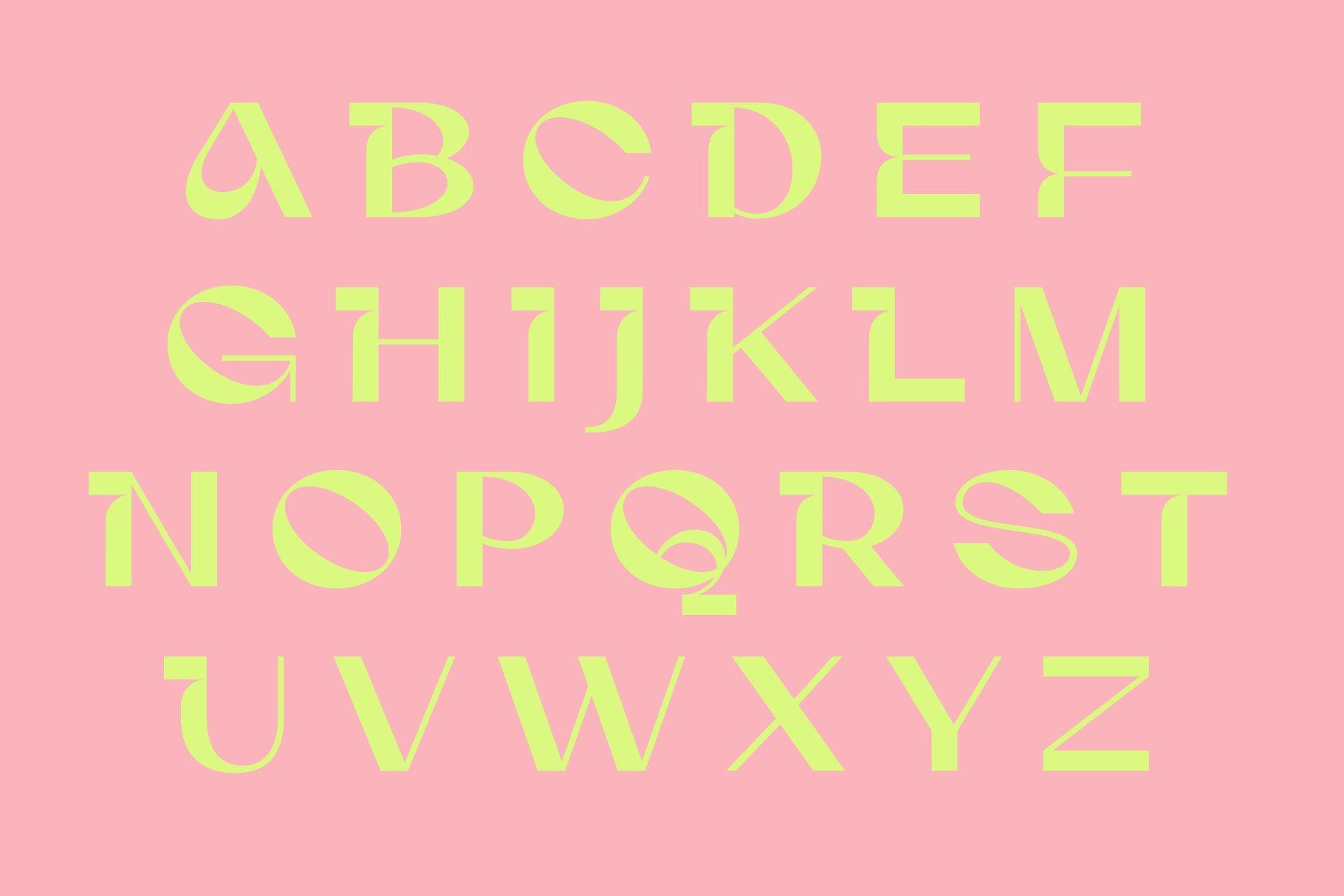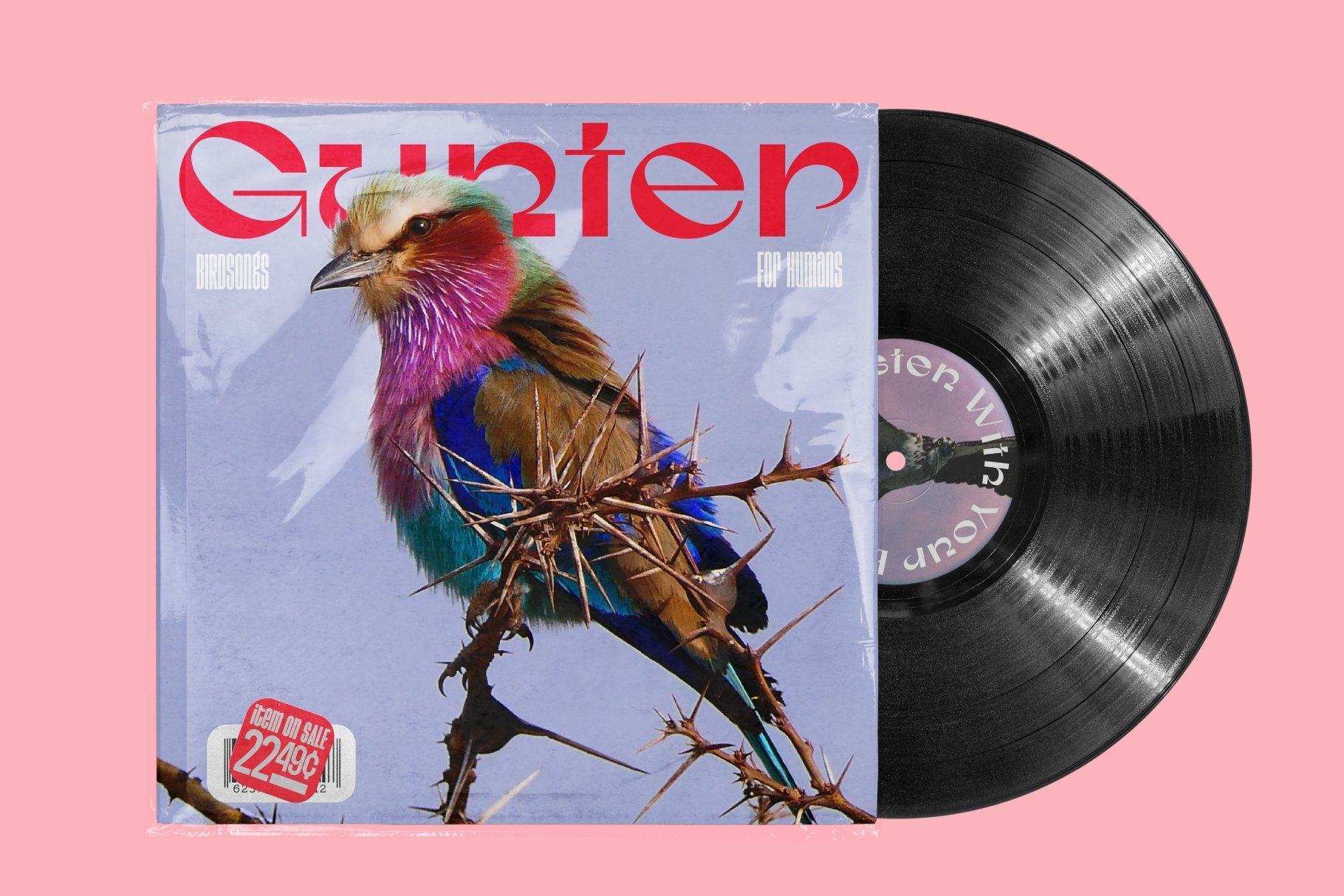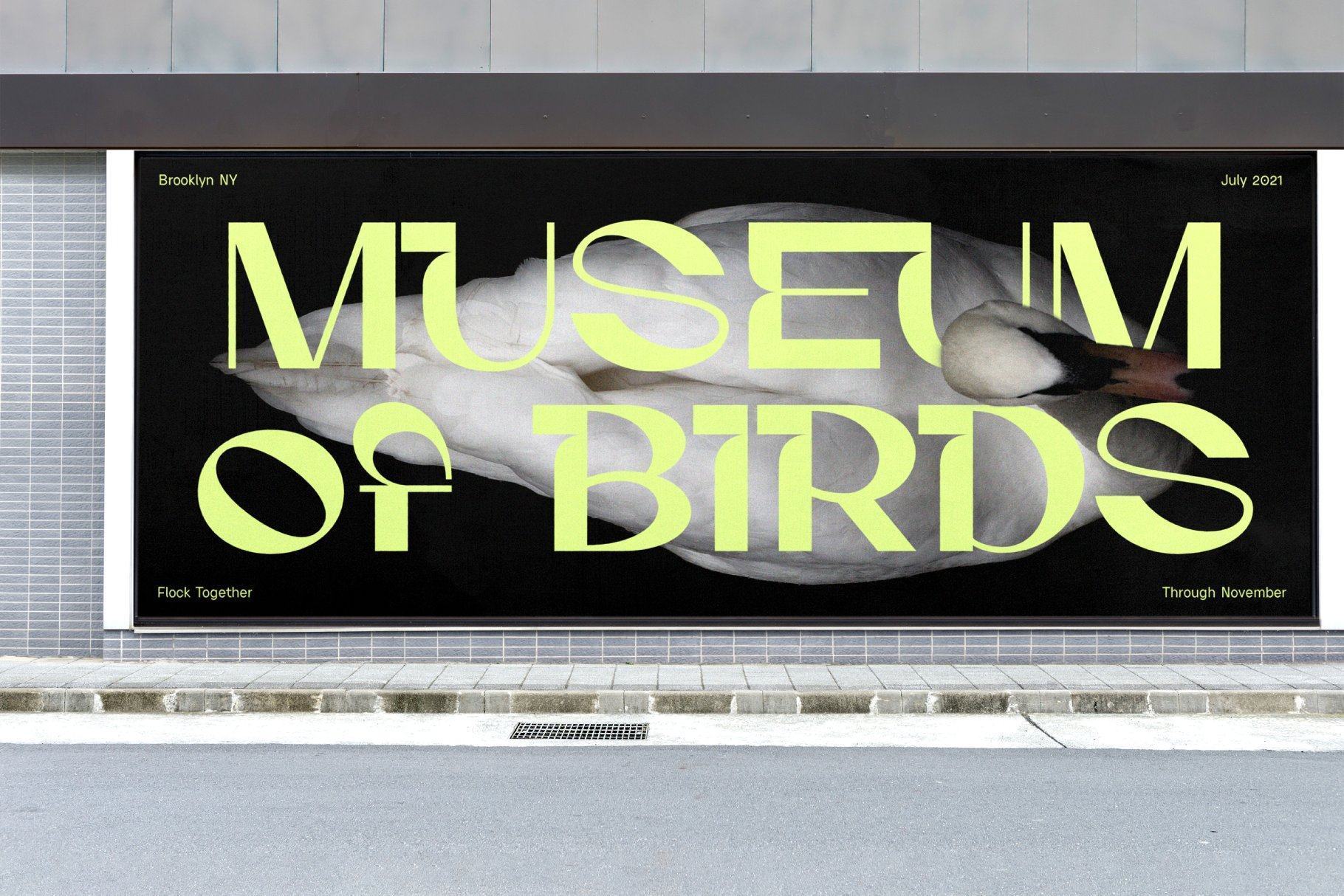
Gunter là một phông chữ hiển thị nửa serif nửa sans serif táo bạo, hiện đại và hiện đại, nằm trong một danh mục riêng. nó có một mặt ngang siêu chắc chắn với những đường cắt và vòng lặp vui nhộn lấy cảm hứng từ thiết kế của những năm 60 và 70. Nó được thiết kế dành cho Social Media vì nó chắc chắn sẽ nổi bật. Nó đi kèm với một bộ phong cách thay thế với những chiếc mũ truyền thống hơn nếu bạn không muốn quá điên rồ.
- 2 kiểu có mũ thay thế
- Chữ hoa và chữ thường
- Đa ngôn ngữ
- Ký hiệu và số